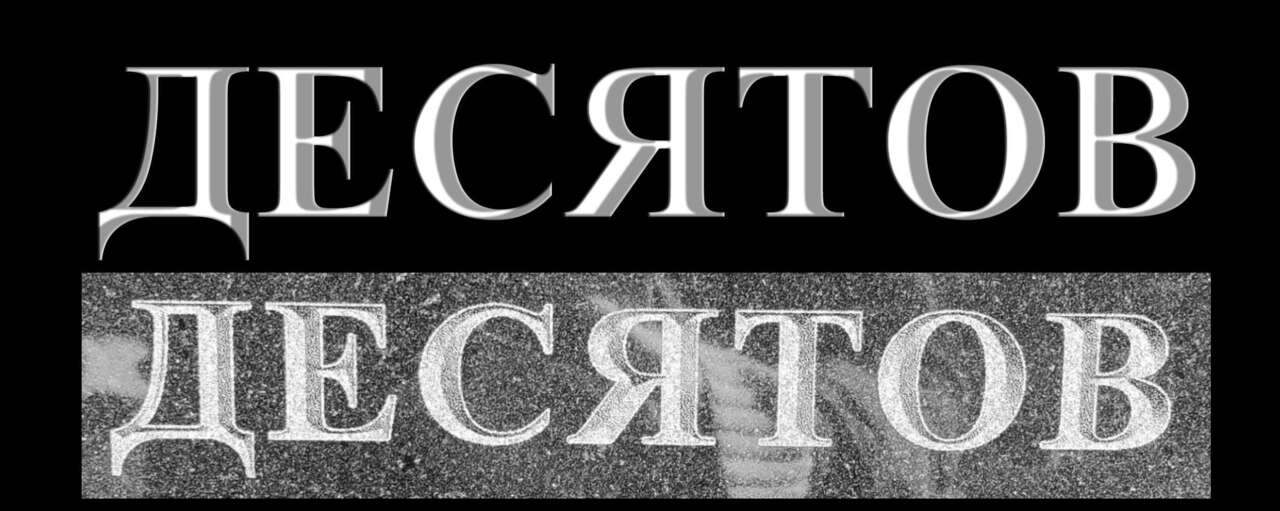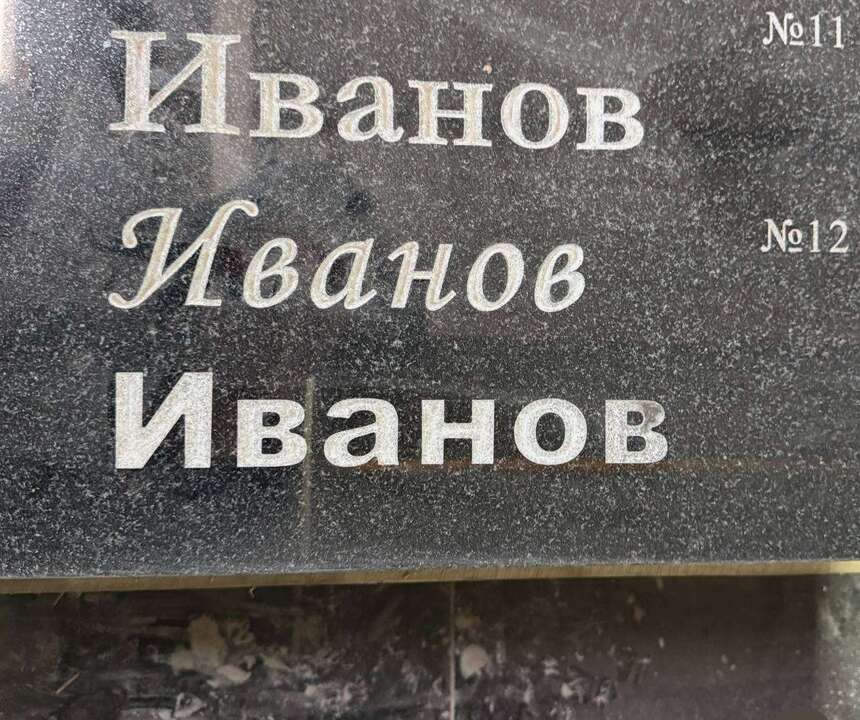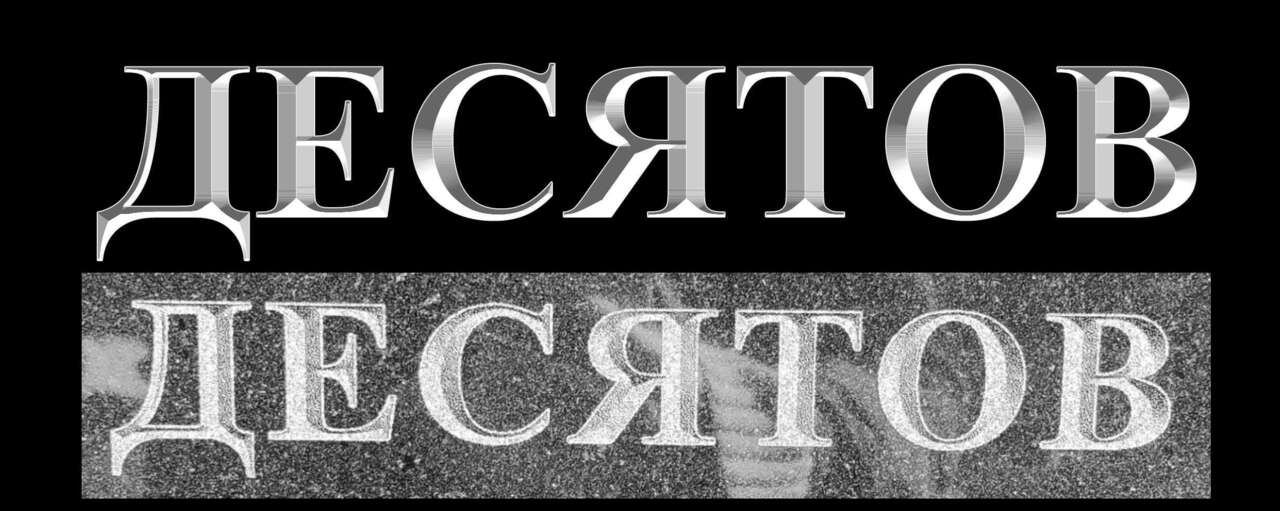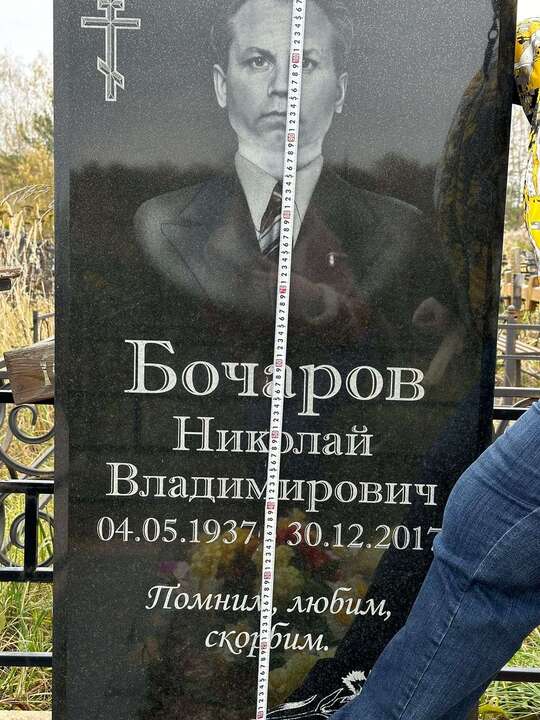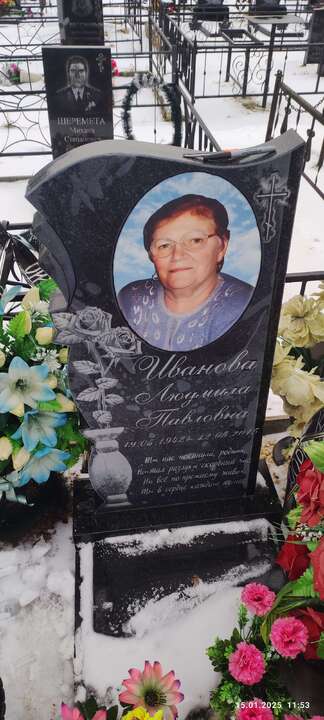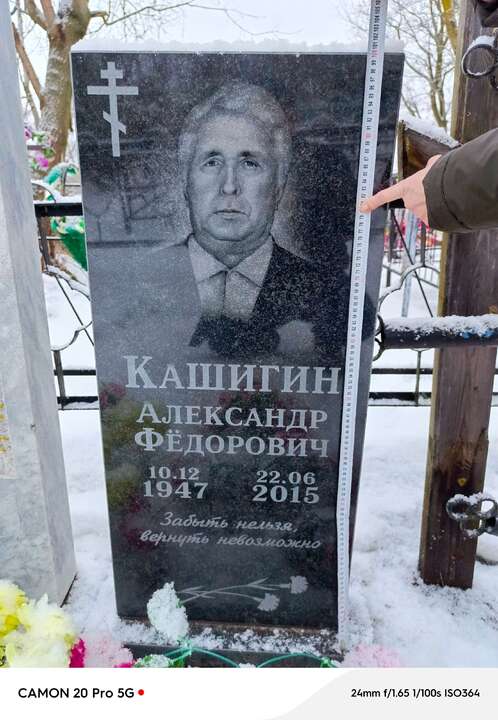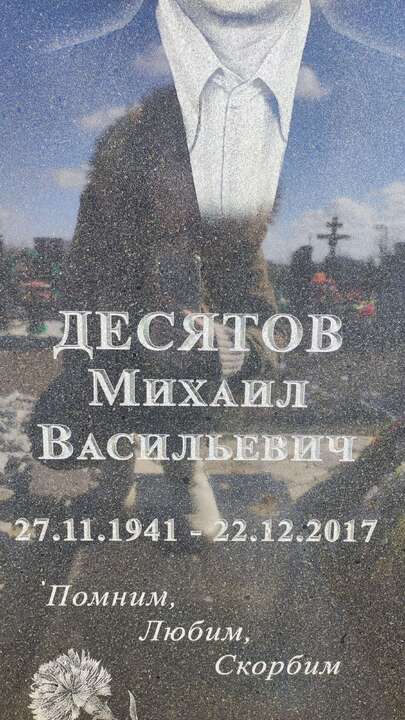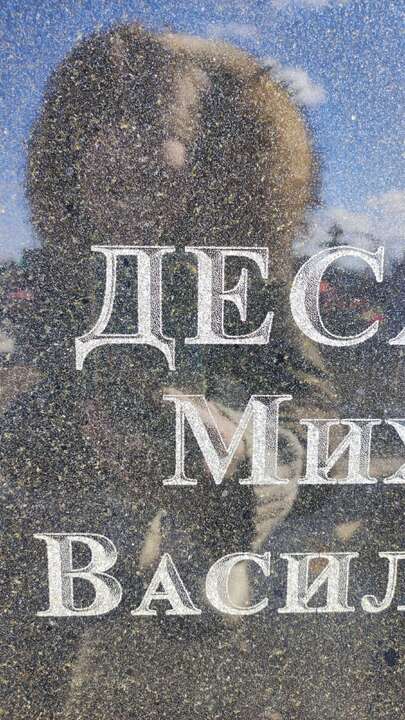
алена Опубликовано 6 февраля, 2025 (изменено) @vadim Многие шрифты пропали..... Попробуй Antiqua-Bold, но Ё придется делать из Е, точки отдельно подрисовывать. @vadim @vadim@vadim Еще вот это посмотри a_AntiqueTrady и Quant Antiqua Bold Изменено 6 февраля, 2025 пользователем алена 2
leekbez Опубликовано 7 февраля, 2025 @АлександрTv Shelly и Adventure @leekbez 2 1
алена Опубликовано 20 февраля, 2025 (изменено) @Владимир65765187 Что не понятно? Академический шрифт + " параметры наложение" - теснение, контур. Изменено 20 февраля, 2025 пользователем алена 1
алена Опубликовано 24 февраля, 2025 @goshanjke Все? №2 Monotype Corsiva №1 Georgia bold или Times New Roman bold №3 Можно a_RubricaCn bold Брусковые как и академические с засечками почти все похожи 1